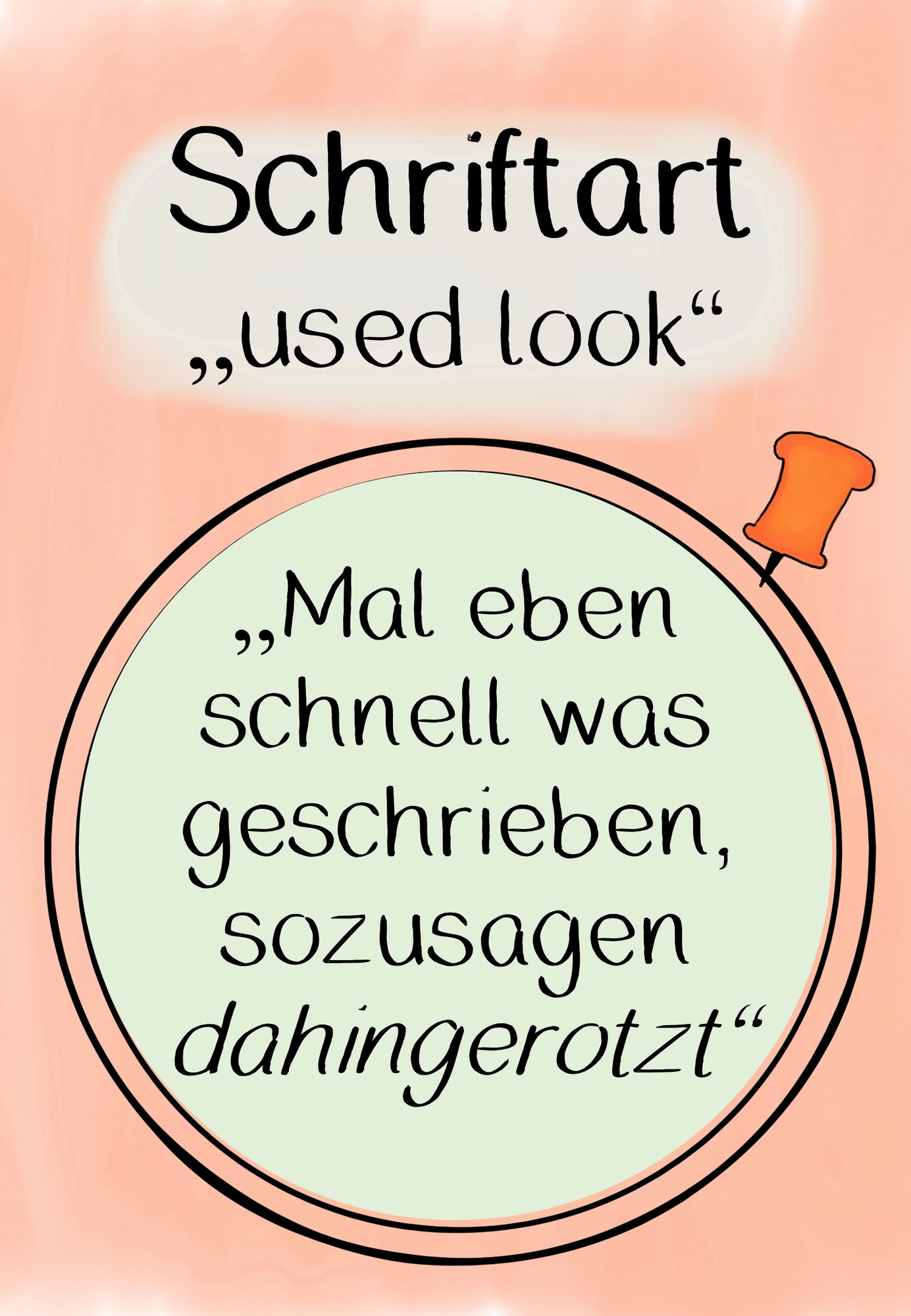
selbst erstellte Schriftarten - Schriftart "Usedlook" - grundschulliebe_s - Deckblatt
Eine Schriftart, die eben nicht perfekt ist sondern ein wenig abgenutzt aussieht.
Schriftart "Usedlook"